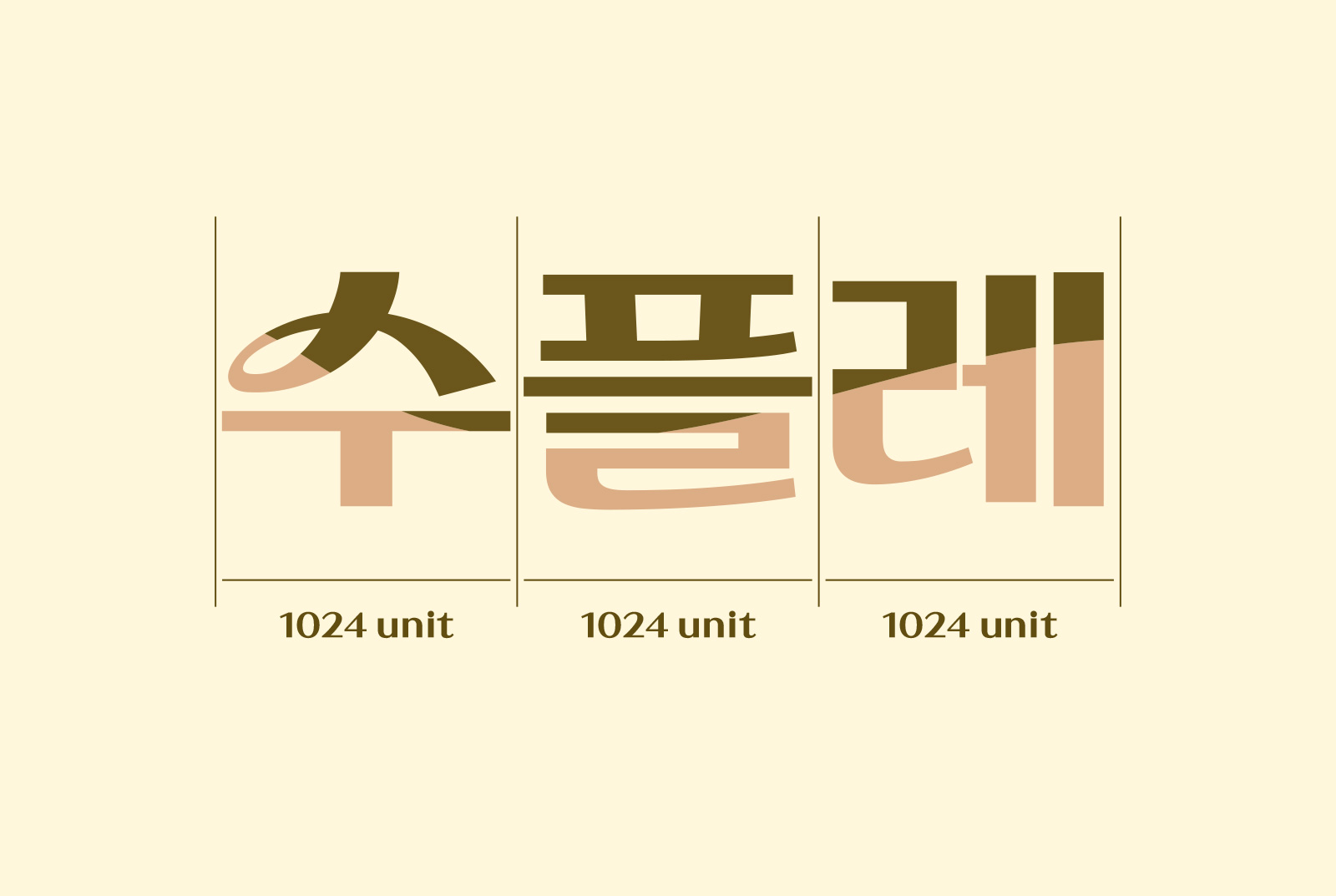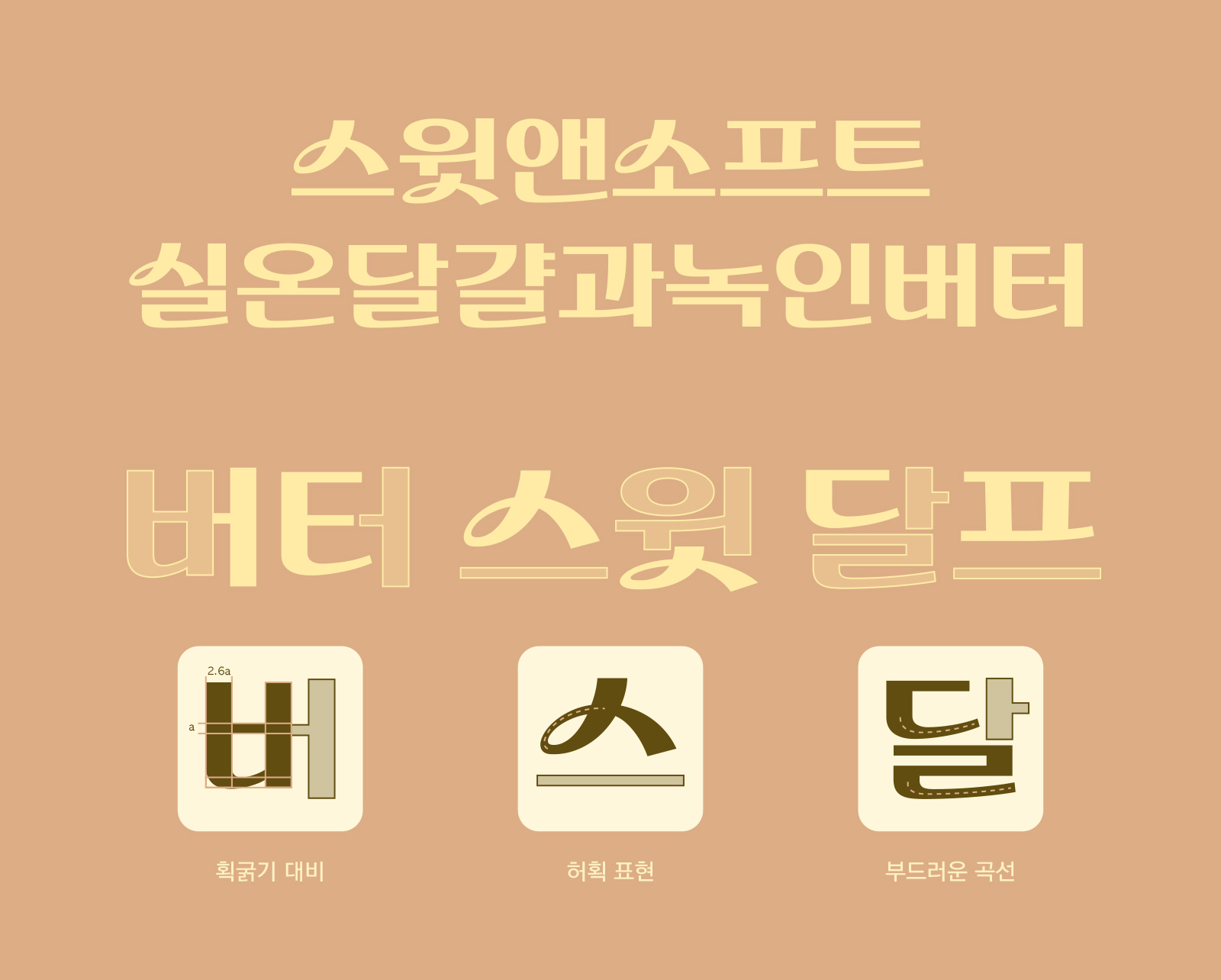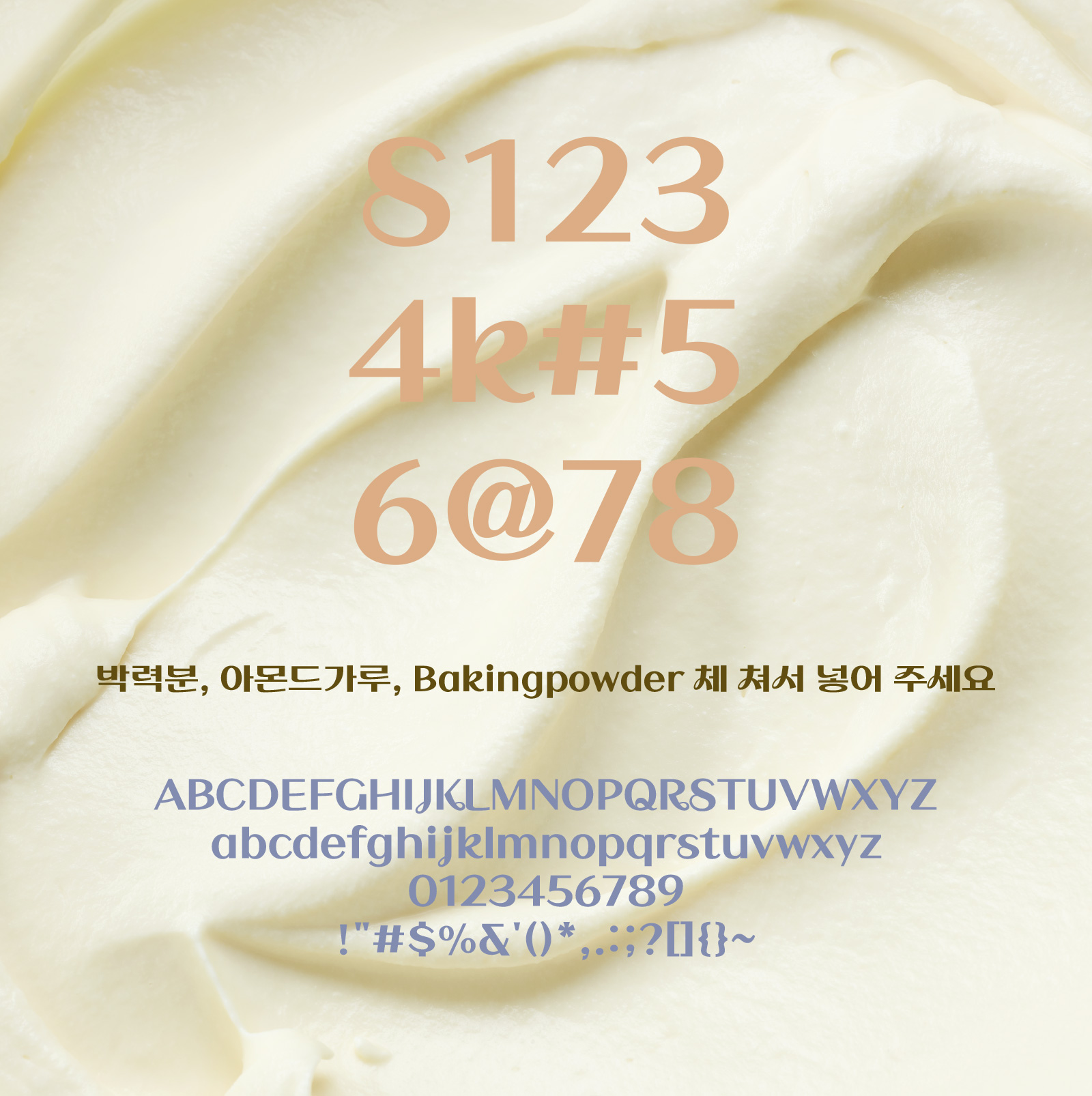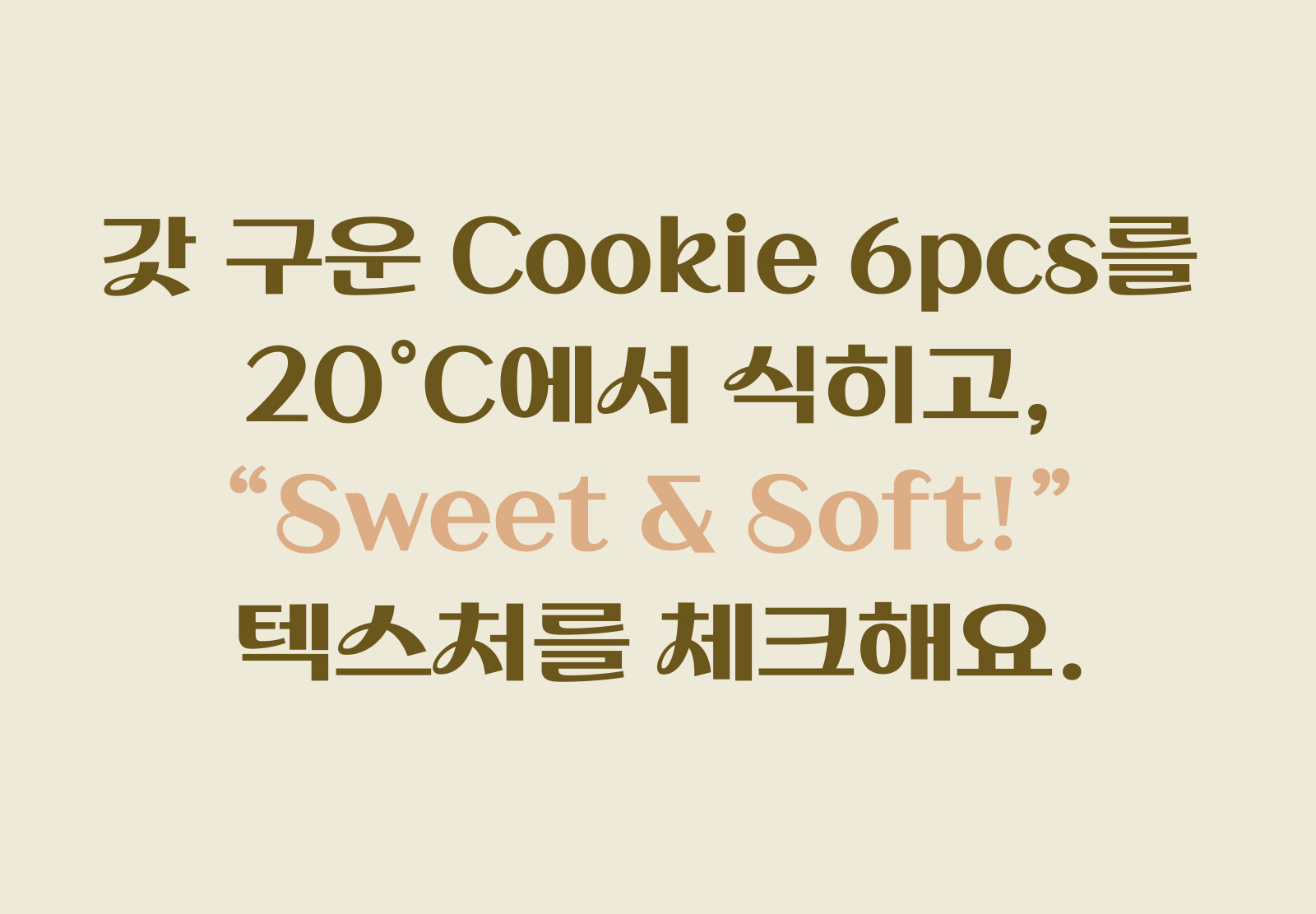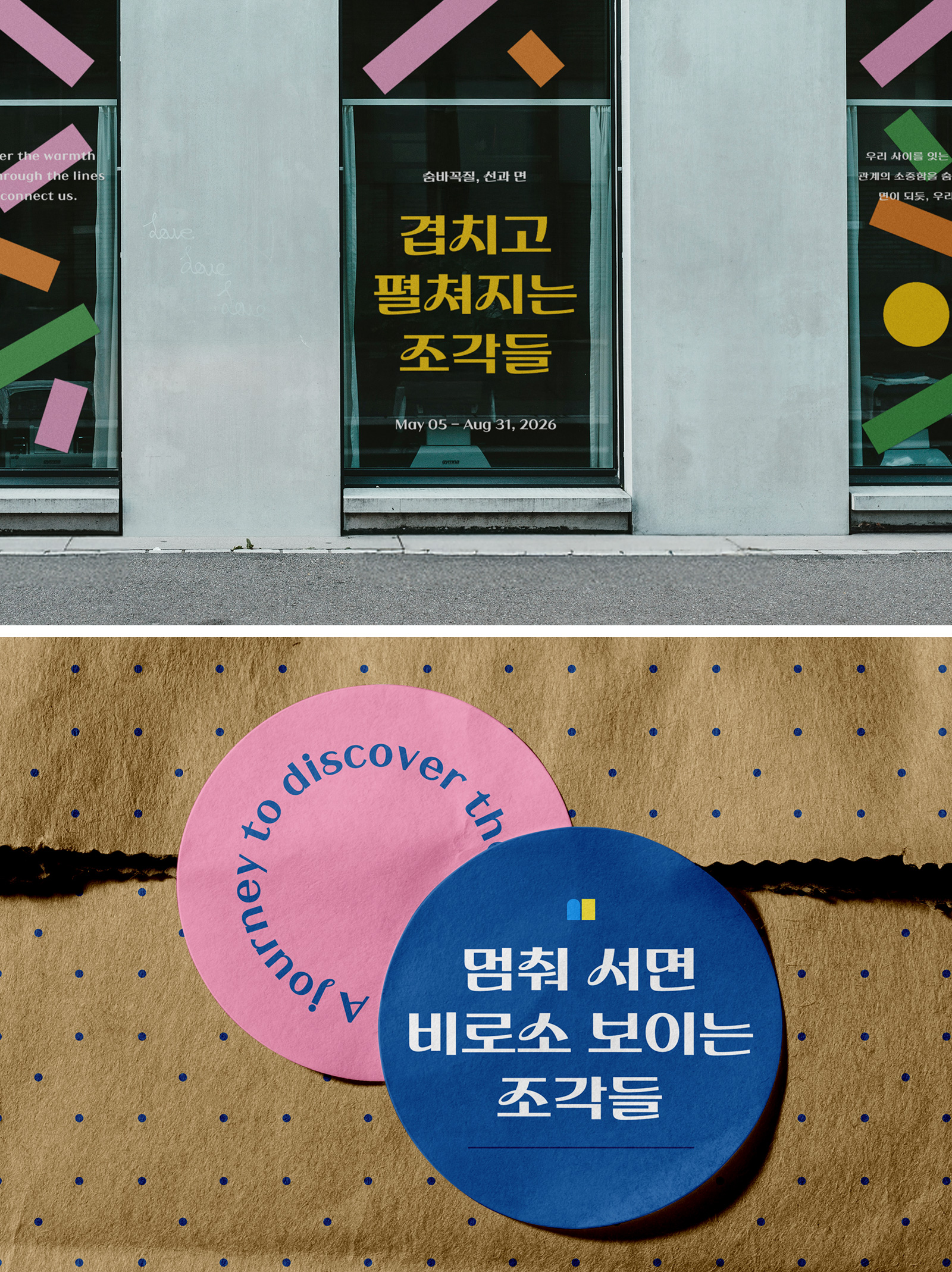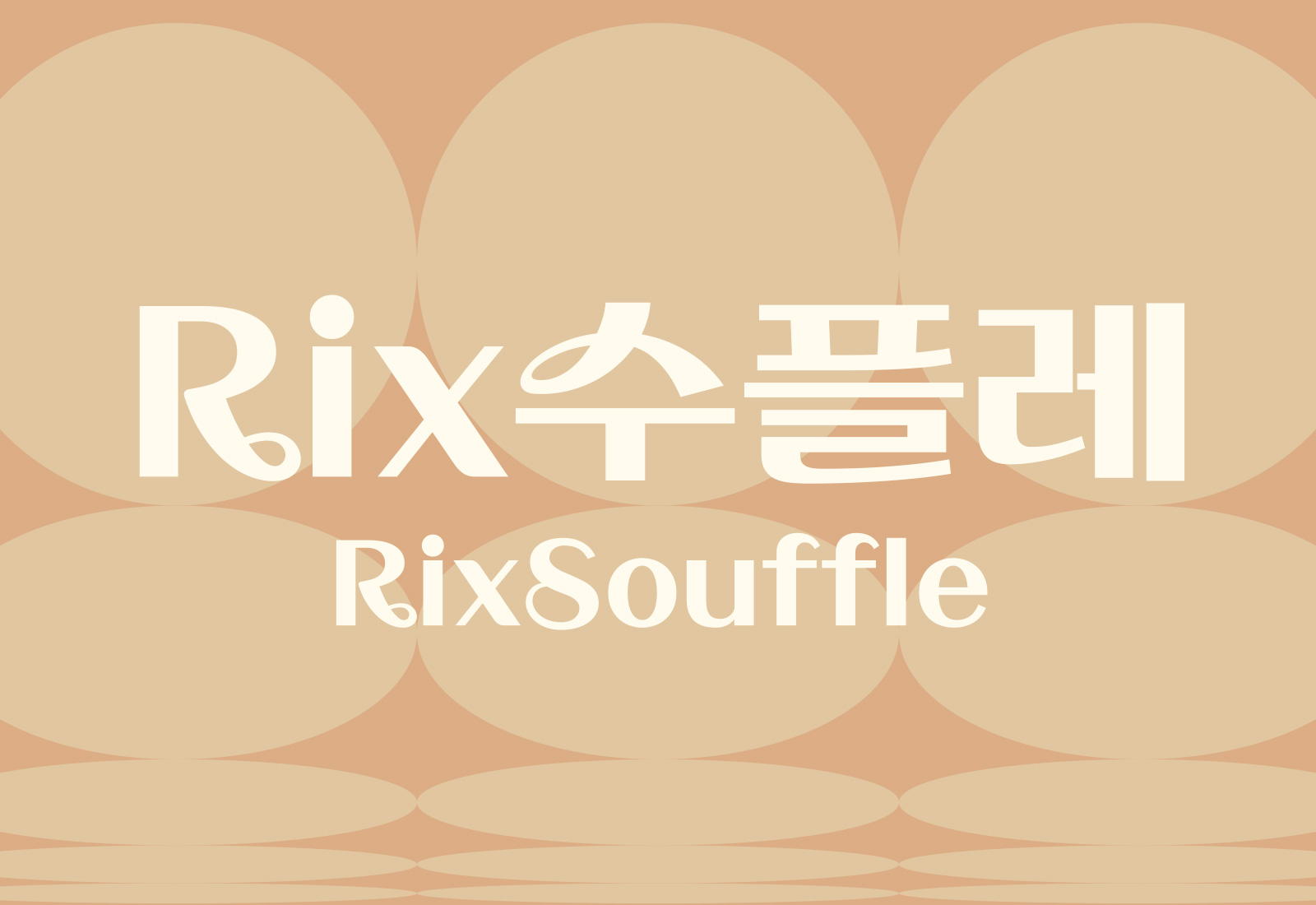
Rix수플레
1 종 - RegularRix수플레는 획 굵기의 대비가 강하고 평이 넓은 그래픽 폰트로, 썸네일이나 헤드라인에 적합한 제목용 폰트입니다.
일부 자소에 포함된 허획과 부드러운 곡선처리가 특징인 폰트입니다.
| 폰트명 | Rix수플레 / RixSouffle |
| 폰트구성 | 한글 2,350자 + 추가자 430자 / 라틴 94자 / 약물 986자 |
넓은 자폭과 꽉 찬 네모꼴 형태
시선을 끄는 획 굵기 대비와 부드러운 획 표현
한글의 특징을 반영한 영문 디자인